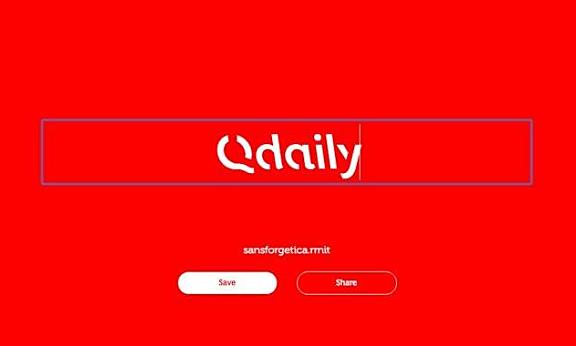
今天要介绍的是Sans Forgetica字体,传说这是一个能提升人的文本记忆力的字体哦,你可以把它应用在你的学习笔记上或者其他的学习途径中。
有人曾经做过一个实验,找来了400个人进行测试,结果得出分别学习 Sans Forgetica 和 Arial 文本的学生,对文本的回忆百分比分别达到 57% 和 50%。
这种字体向左边倾倒 8 度(反倾斜),在笔触的关键位置有截断,一贯靠辨识字母外围阅读的读者可以通过想象将其补完。